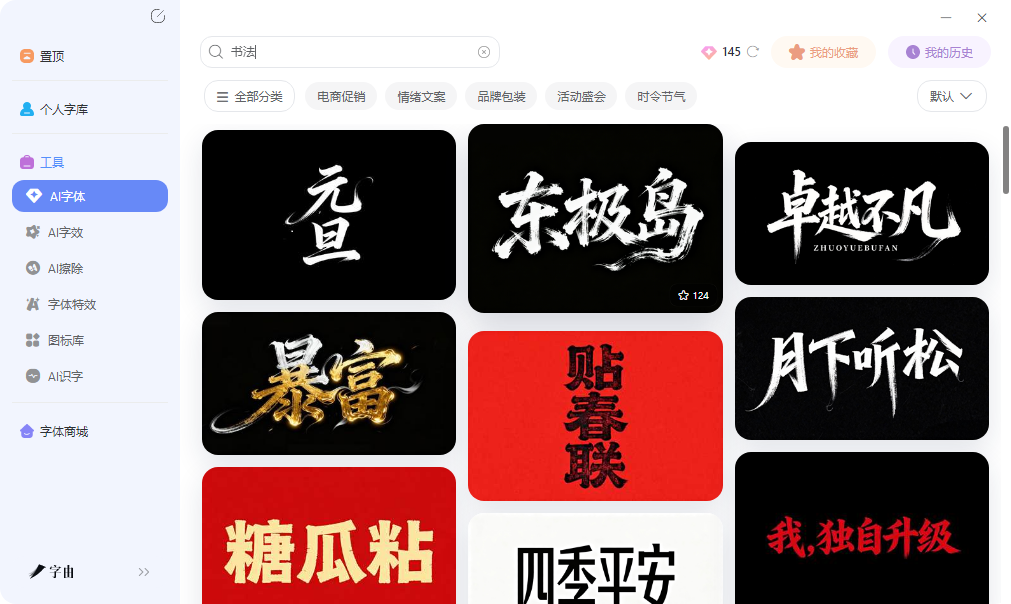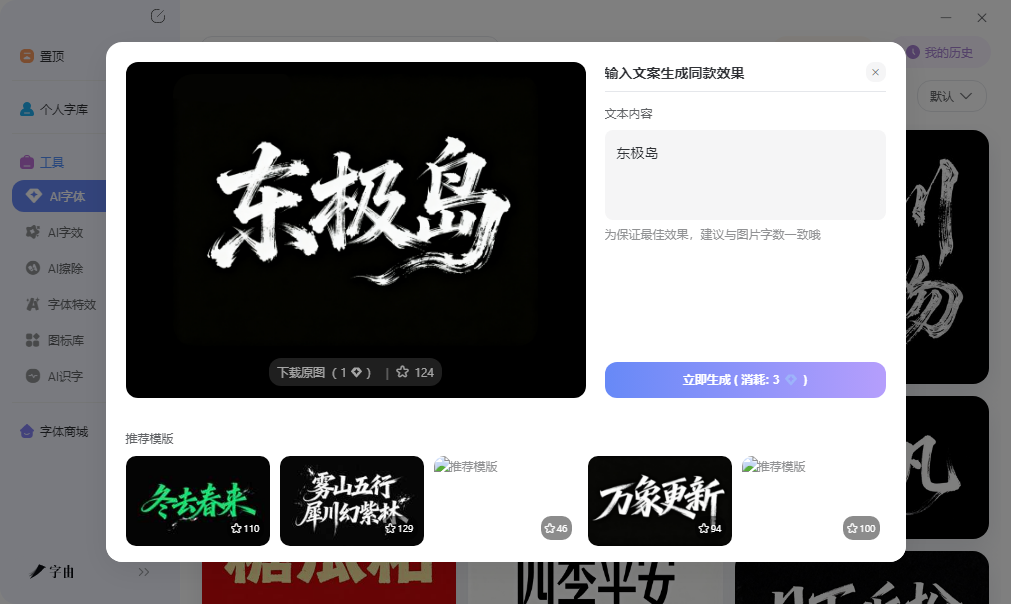
行书字体转换器在线生成,输入文字直接转行书
做海报标题、设计Logo、排印刷品,行书字体是常用的选择。它的特点是笔画连贯、书写速度快,介于楷书的规整和草书的狂放之间,既有辨识度又有艺术感。但电脑默认字体里也没有几款像样的行书体。而字由客户端提供了三种独立的行书转换方式,分别适用于不同场景,操作路径和输出结果都不一样。今天的文章会介绍具体的操作步骤、适用场景、优缺点以及与传统方法的对比。
1、字由AI字体功能
字由的AI字体功能内置了手写书法风格模板,其中一部分是行书和行楷风格。这些模板的字体、特效、排版和背景参数已经全部预置好。用户不需要手动调节任何参数,也不需要具备设计软件操作经验。
具体操作步骤:打开字由客户端,在顶部导航栏进入AI工具模块,找到AI字体页面。模板按风格分类,包括国潮风、手写书法、电商促销等。选择手写书法分类,系统展示该分类下的所有模板。每个模板的预览图中可以看到字体的笔画特征和整体风格。用户输入自己的文案后,选择一个模板,点击生成按钮,系统输出一张PNG格式的图片。图片背景透明,可以直接放进海报或封面中使用。生成一张图片消耗3个算力点,每日登录赠送6个点。
常见问题:如果生成的图片中文字排版不协调,可能是因为用户输入的字符数与模板示例的字符数相差太多。解决方法是尽量保持字符数一致,或者选择字符数更接近的模板重新生成。如果对笔画风格不满意,可以更换模板重新生成。由于AI字体消耗算力点,用户可以先在预览模式中快速浏览模板效果,确认喜欢后再生成正式图片,避免浪费点数。
传统方式需要用户打开PS,选一款行书字体,然后手动添加阴影、描边、背景等特效。调一个参数要试好几次,半小时不一定能调出满意效果。字由AI字体把字体、特效、排版全部打包好,用户只需要做选择,不需要做调试。
2、激活字体库:一键替换字体
字由字体库中收录了多款行书和行楷字体。用户打开字由客户端,在搜索框输入“行书”或“行楷”等关键词,系统列出所有相关字体。每款字体都可以在线预览——输入自己的文案,页面实时显示该字体的效果。找到需要的字体后,点击“激活”按钮。激活后,该字体自动出现在Photoshop、Illustrator、Word等软件的字体列表中。用户在设计软件中输入文字,选择该字体,即可自由编辑、排版、调节字号和颜色。
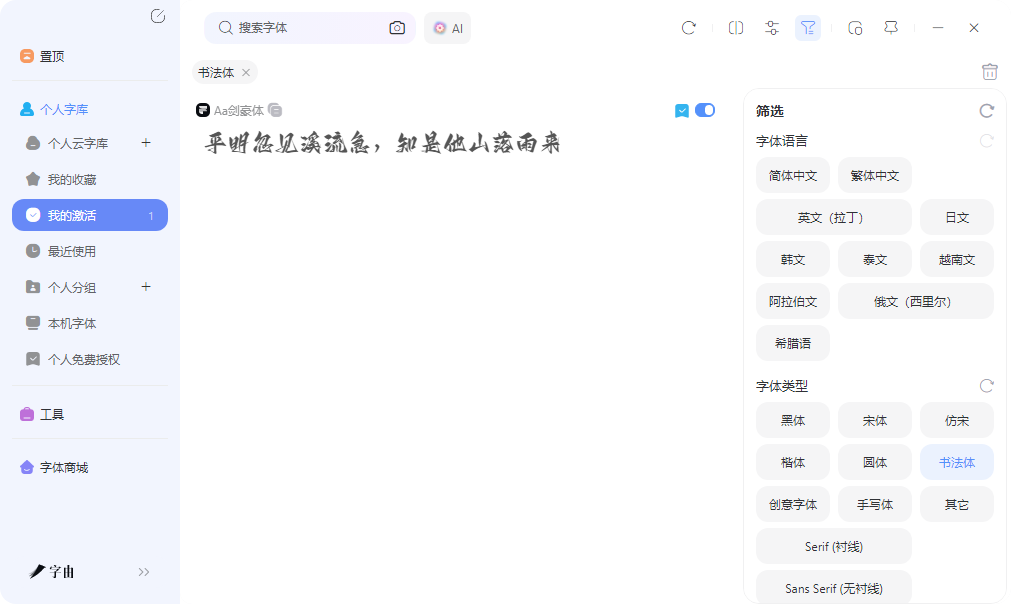
具体操作步骤:第一步,在字由客户端左侧筛选栏的字体类型中勾选“书法体”,然后在语言筛选中勾选“简体中文”。第二步,在搜索框输入“行书”或“行楷”,浏览结果列表。第三步,在预览框中输入自己的文案(例如品牌名或常用短句),页面会显示该字体应用到文案上的真实效果。第四步,点击字体卡片上的“激活”按钮,按钮从灰色变为绿色,表示激活完成。第五步,打开PS或Word,在字体下拉菜单中找到该字体,输入文字即可使用。
适用场景举例:品牌VI手册需要长期使用同一款行书字体作为标题字体;系列海报每期都要用同款行书字体打不同的活动主题;书籍封面需要反复调整行书标题的位置和大小。这些场景的共同点是:需要反复编辑文字内容,字体需要长期可调用。
3、实时预览:在线输入文字,即时切换行书字体效果
字由客户端提供了一个轻量的字体预览工具,进入字体库页面。选择一个字体分类或在搜索框输入关键词,系统列出符合条件的字体列表。用户在预览区域输入自己的文案,点击任意字体,页面即时切换显示该字体应用到文案上的效果。
具体操作步骤:第一步,打开字由,点击登录(支持微信扫码或手机号登录)。第二步,在顶部搜索框输入“行书”或“行楷”,或者在左侧筛选栏的字体类型中勾选“书法体”。第三步,在预览区域(通常是一个文本框)中输入自己的文案,例如“春风十里”。第四步,点击任一字体卡片,预览区域会自动显示该字体应用到“春风十里”上的效果。第五步,依次点击其他字体卡片,对比不同行书字体的笔画特征、字间距、整体气质。第六步,确定喜欢的字体后,可以记下字体名称,再到客户端中搜索激活。
三种方式任你选择:AI字体适合需要快速输出标题图片的场景,不需要后续编辑,操作路径最短。激活字体库适合需要在PS和Word中长期使用同一款行书字体的项目,激活后字体可随时调用,支持多设备同步。实时预览适合字体选型阶段,用来快速对比不同字体的显示效果,确认后再激活。用户可以根据当前需求选择对应的方式,也可以在同一个项目中组合使用。三种方式的共同点是:不需要下载字体文件,不需要手动安装,不需要重启软件,这将会大大地提升你的工作效率。